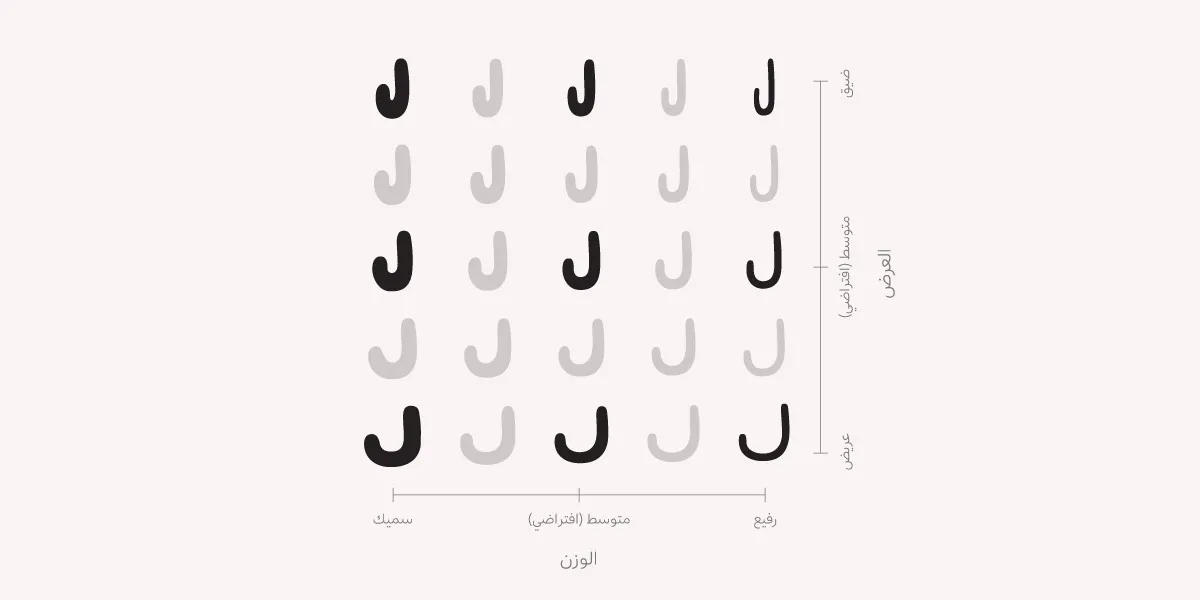
الخطوط المتغيِّرة، وتجارب بصريِّة جديدة
استخدام الخطوط المتغيِّرة لتصميم خطوطٍ عربيَّة أكثر مرونة.
إذا كنت مصممًا، فربما سمعت عن الخطوط المتغيرة أو شاهدت استخدامًا لها لفت انتباهك. جذبتني الخطوط المتغيرة أيضًا كمصممة خطوط، وبدأت البحث عنها واستكشفت مزاياها وطرق توظيفها في تطوير الخطوط العربية.
لذا أكتب هذا المقال كدليلٍ مصورٍ ومبسط لك أيضًا، آملةً أن يساعدك على فهم الخطوط المتغيرة، وطرق استخدامها في التصميم.
الخطوط المتغيرة، والخطوط الثابتة التقليدية
الخطوط المتغيرة تقنية تدمج عائلة خط كاملة في ملف خط واحد. يشمل الخط المتغير الواحد أنماطًا وأوزانًا متعددة للخط، ويمنح المصمم خيارات غير محدودة للتحكم بنمط الخط، على غرار الخطوط الثابتة (التقليدية).
تقليديًا، تُفصل أوزان الخطوط وأشكالها إلى ملفات خطوط مختلفة، فيحتاج المصمم أن يثبت ملفات خطوط فردية لكل شكل. مثلًا، إذا كانت عائلة خط «ربيع» الكامل مكونة من أربعة ملفات خطوط ثابتة: ربيع الرفيع، ربيع العادي، ربيع المتوسط، ربيع السميك - فإنَّ خط «ربيع» المتغيّر ملف واحد فقط؛ إذ ليس على المصمم سوى أن يثبت ملفًا واحدًا: ربيع المتغير. يمكن أن يحدد المصمم بعد ذلك وزن الخط بدقة - المتدرج من رفيع إلى سميك - في برامج التصميم بناءً على الحاجة.
رسوم خط ربيع الأولية للوزن السميك
مقارنة بين خط ثابت وخط متغير
يضيف مصمم الخط صفات متغيرة إلى الخط (مثل صفة الوزن) بإضافة محاور متغيرة، وينسب إلى المحور قيمة دنيا (أرفع وزن)، وقيمة قصوى (أسمك وزن)، وقيمة افتراضية (وزن متوسط مثلًا.) ثم يتحكم مستخدم الخط بوزن الخط المتغير بتغيير قيمة محور الوزن.
رسوم خط ربيع الأولية للوزن السميك
أشكال حرف اللام المنفصلة في خط متغير في محوري الوزن والعرض
ماذا نستفيد من استخدام خط متغير؟
١ تقليص حجم ملف الخط
جميع أوزان الخط تُضغط في ملف خط متغير واحد حجمه أصغر بكثير من مجموع حجم ملفات الخط الفردية الثابتة في عائلة الخط. هذه فائدة ملحوظة خصوصًا عند استخدام الخط كخط ويب؛ فاستخدام خط متغير واحد بدلاً عن مجموعة خطوط ثابتة يقلل زمن تحميل الخط في صفحات الإنترنت، مما يُسرِّع تصفح الويب.
٢ التحكم بنمط الخط بحرية
لمستخدم الخط أن يحدد نمط الخط (وزن/شكل/…) بدقة بتغيير قيمة محور النمط المعين مباشرةً. مثلًا إذا كان الوزن الرفيع ممثلًا بالقيمة 200، والنحيف 300، وأراد المستخدم وزنًا بين الاثنين - يمكن أن يحدد للمحور قيمة وسيطة كـ 240، أو 250، أو 260. بهذا يحصل المستخدم على وزن وسيط بين الرفيع والنحيف يحدد سماكته بدقة بتغيير قيمة محور الوزن صعودًا ونزولًا.
رسوم خط ربيع الأولية للوزن السميك
حرف النون المنفصل الرفيع (200) والنحيف (300) وأوزان وسيطة بينهما
٣ تحريك الخطوط المتغيرة في الويب
الخطوط المتغيرة قابلة للتحريك في الويب باستخدام تحريكات CSS برمجية بسيطة. يمكن إضافة تأثيرات وانتقالات تفاعلية سلسة إلى النصوص في الويب لتُحسِّن التصميم وتجربة المستخدم.
رسوم خط ربيع الأولية للوزن السميك
نصوص تتغير تدريجيًّا عندما يمرر المستخدم الصفحة إلى الأعلى أو الأسفل
رسوم خط ربيع الأولية للوزن السميك
روابط تتغير عند التمرير عليها بالمؤشر
رسوم خط ربيع الأولية للوزن السميك
إضافة تحريكات نصوص باستخدام الخطوط المتغيرة
٤ تسهيل القراءة الرقمية
تحسِّن الخطوط المتغيرة تصميم الويب من ناحية أخرى، وهي أنها تُستعمل أيضًا لتغيير الحجم البصري للنصوص تلقائيًا في المتصفحات. تتغير سماكة أشكال الحروف بناءً على حجم الخط؛ تزيد السماكة قليلًا في الأحجام الصغيرة وتُضبط بصريًا لضمان أنها قابلة للقراءة. أما في الأحجام الكبيرة يزيد التباين في إطار الحرف ليخدم أغراضًا جمالية عند استخدامه في العناوين والنصوص المهمة.
رسوم خط ربيع الأولية للوزن السميك
الفرق بين تباين سماكة إطار الحروف في الأحجام الصغيرة والكبيرة
«محاور» الخطوط المتغيرة
يشير المحور في الخطوط المتغيرة إلى كل صفة قابلة للتغيير، ويمكن أن يحتوي الخط المتغير الواحد على عدة محاور يضبطها المستخدم تبعًا لحاجته.
أكثر المحاور شيوعًا محور الوزن، وهو أحد المحاور الخمسة الأساسية: الوزن، والعرض، والحجم البصري، والانحراف، والميلان. حري بالذكر أن للمحاور أنواعًا أخرى، ويمكن إضافة محاور مُخصصة حسب تقدير مصمم الخط. كل محور يُرمز إليه بأربعة أحرف لاتينية، وفي ما يلي شرح لبعض المحاور:
محور الوزن - Weight axis (wght)
يتحكم محور الوزن بسماكة إطار حروف الخط، ويتدرج من أرفع وزن للخط إلى أغلظ وزن فيه. تتباين قيم هذا المحور من خط إلى آخر، ولكن في الغالب يُنسب إليه نطاق قيم من 100 (رفيع) إلى 800 (غليظ،) ويحدد الوزن الافتراضي بـ 400 (عادي).
محور الوزن
محور العرض - Width axis (wdth)
يتحكم هذا المحور بالمساحة الأفقية التي تحتلها أحرف الخط، حيث إنه يتدرج من ضيق إلى عريض. تُمثَّل قيمة العرض الافتراضي في محور العرض عادةً بالقيمة 100، وتزيد وتنقص لتمثّل الأشكال الأعرض والأضيق.
محور العرض
محور الانحراف - Slant axis (slnt)
يتحكم  محور الانحراف بزاوية أشكال الحروف. يُمثَّل الشكل العمودي (العادي) للحرف بالقيمة صفر درجة، وتتدرج صعودًا ونزولًا لتعبِّر عن انحراف الخط إلى اليمين أو اليسار.
محور الانحراف
محور الميلان - Italic axis (ital)
يتحكم هذا المحور بميلان الخط، إذ يمكن تفعيله (مائل) أو تعطيله (عادي)، ولا يتدرج عبر نطاق كسابقاته. يختلف هذا المحور عن محور الانحراف في أنه يٌفعِّل شكلًا مصممًا خصيصًا للاستخدام في النصوص المائلة، أمّا الأشكال الناتجة عن تغيير محور الانحراف فهي نفس أشكال الخط العادي مُمالة بزاوية إلى اليمين أو اليسار.
مفهوم استخدام شكلين (عادي ومائل) في النصوص سائد في الكتابة اللاتينية لتوضيح الأجزاء المهمة في النص.
الخطوط المتغيرة فرصة لاستكشاف تجارب بصرية جديدة في اللغة العربية تحديدًا؛ فنظام الكتابة العربي مرن يتقبل ويتيح خيارات لاستخدامه بأساليب منوعة ومبتكرة. أتطلع شخصيًّا إلى أن أتابع تطور تقنيات صناعة الخطوط العربية واستخدام المصممين لها. :)